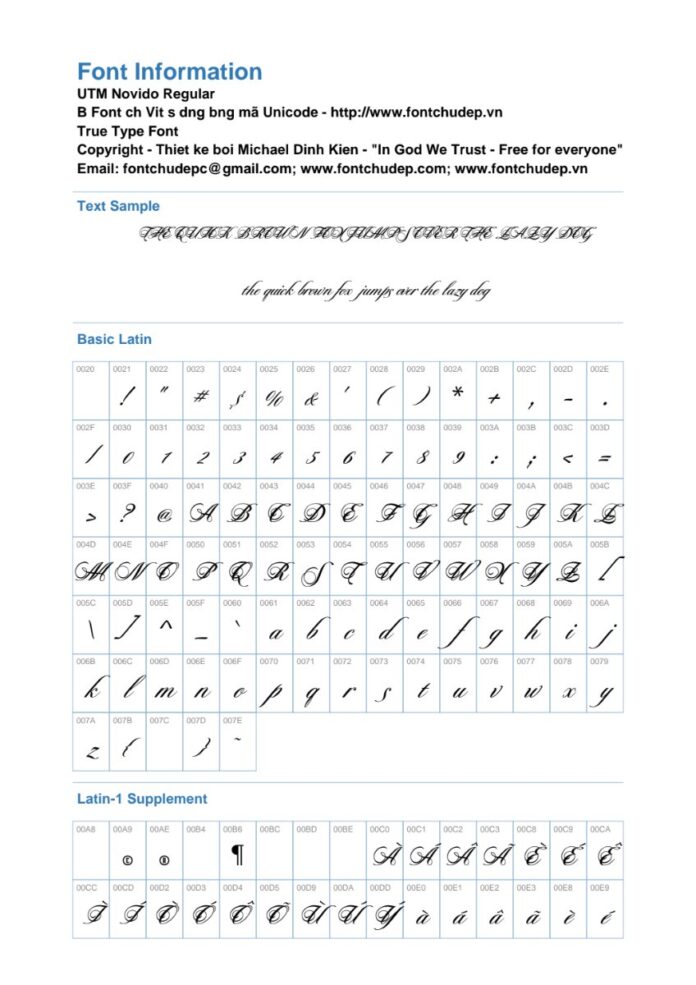
Trong thế giới thiết kế đồ họa, việc lựa chọn font chữ phù hợp đóng vai trò cực kỳ quan trọng, quyết định đến tính thẩm mỹ và thông điệp mà tác phẩm muốn truyền tải. Trong số vô vàn các lựa chọn, font chữ UTM Novido nổi bật như một viên ngọc quý, mang đến sự mềm mại, uyển chuyển và đầy tính nghệ thuật. Tại Poster.vn, chúng tôi tự hào giới thiệu và cung cấp tài nguyên font chữ chất lượng cao này, giúp các nhà thiết kế dễ dàng tạo ra những sản phẩm độc đáo và ấn tượng.
Giới Thiệu Chung Về Font UTM Novido
Font UTM Novido là một kiểu chữ viết tay (script font) được thiết kế với những đường nét mềm mại, uyển chuyển và bay bổng. Đây là một trong những font chữ được ưa chuộng bởi khả năng tạo ra cảm giác sang trọng, tinh tế và đầy cảm xúc. Với bộ ký tự đa dạng, hỗ trợ tiếng Việt đầy đủ (UTM Novido Regular), font chữ này trở thành lựa chọn lý tưởng cho nhiều loại hình thiết kế khác nhau, từ thiệp mời, logo, bao bì sản phẩm cho đến các ấn phẩm quảng cáo.
Đặc Điểm Nổi Bật Của Font UTM Novido
- Thiết kế mềm mại, bay bổng: Các ký tự của UTM Novido được tạo hình với những đường cong uyển chuyển, mang lại vẻ đẹp thanh lịch và lãng mạn.
- Hỗ trợ tiếng Việt đầy đủ: Đây là một điểm cộng lớn, giúp các nhà thiết kế Việt Nam dễ dàng sử dụng mà không lo lỗi font hay thiếu ký tự.
- Tính ứng dụng cao: Phù hợp với nhiều phong cách thiết kế, từ cổ điển đến hiện đại, từ tối giản đến phức tạp.
- Dễ đọc: Mặc dù là font viết tay, UTM Novido vẫn đảm bảo tính dễ đọc, giúp truyền tải thông điệp một cách rõ ràng.
Ứng Dụng Của Font UTM Novido Trong Thiết Kế
Với những ưu điểm vượt trội, font UTM Novido có thể được ứng dụng linh hoạt trong nhiều lĩnh vực thiết kế khác nhau:
Thiết Kế Logo và Nhận Diện Thương Hiệu
Font UTM Novido mang đến sự độc đáo và cá tính cho các thiết kế logo. Đặc biệt phù hợp với các thương hiệu muốn thể hiện sự sang trọng, tinh tế, hoặc có yếu tố thủ công, nghệ thuật. Một logo sử dụng UTM Novido sẽ dễ dàng tạo ấn tượng mạnh mẽ và khó quên.
Thiệp Mời, Thiệp Chúc Mừng
Với vẻ đẹp lãng mạn và bay bổng, UTM Novido là lựa chọn hoàn hảo cho các loại thiệp mời cưới, thiệp sinh nhật, thiệp chúc mừng. Font chữ này giúp tăng thêm sự trang trọng và cá nhân hóa cho mỗi tấm thiệp.
Bao Bì Sản Phẩm
Các sản phẩm cao cấp, mỹ phẩm, đồ handmade, hoặc thực phẩm chức năng thường tìm kiếm một font chữ có thể truyền tải sự tinh tế và chất lượng. UTM Novido hoàn toàn đáp ứng được yêu cầu này, giúp bao bì sản phẩm trở nên thu hút và đẳng cấp hơn.
Ấn Phẩm Quảng Cáo và Marketing
Trong các chiến dịch quảng cáo, banner, poster, hoặc các ấn phẩm truyền thông, UTM Novido có thể được sử dụng để tạo điểm nhấn, thu hút sự chú ý của người xem. Đặc biệt hiệu quả khi kết hợp với các hình ảnh và màu sắc phù hợp.
Thiết Kế Sách, Tạp Chí và Website
Đối với các tiêu đề, trích dẫn hoặc các phần nội dung cần sự nổi bật, UTM Novido sẽ là một lựa chọn tuyệt vời. Nó mang lại cảm giác nghệ thuật và chuyên nghiệp cho các ấn phẩm in ấn và kỹ thuật số.
Hướng Dẫn Sử Dụng Font UTM Novido Hiệu Quả
Để tận dụng tối đa vẻ đẹp của font UTM Novido, bạn cần lưu ý một số điểm sau:
- Kết hợp hài hòa: Nên kết hợp UTM Novido với các font chữ sans-serif hoặc serif đơn giản để tạo sự cân bằng và dễ đọc. UTM Novido thường phù hợp làm tiêu đề hoặc điểm nhấn, trong khi các font khác sẽ đảm nhiệm phần nội dung chính.
- Kích thước phù hợp: Do tính chất là font viết tay, UTM Novido thường đẹp nhất ở kích thước lớn hơn một chút so với các font chữ thông thường, giúp các đường nét uyển chuyển được hiển thị rõ ràng.
- Màu sắc: Lựa chọn màu sắc phù hợp sẽ làm nổi bật vẻ đẹp của font. Các tông màu pastel, màu vàng đồng, hoặc màu đen trên nền sáng thường rất hiệu quả.
- Khoảng cách chữ (Kerning): Điều chỉnh khoảng cách giữa các ký tự một cách hợp lý để đảm bảo tính thẩm mỹ và dễ đọc.
Font UTM Novido phù hợp với loại hình thiết kế nào?
Font này rất phù hợp cho thiết kế logo, thiệp mời, bao bì sản phẩm, tiêu đề ấn phẩm, banner quảng cáo, và các dự án cần sự mềm mại, sang trọng và tinh tế.